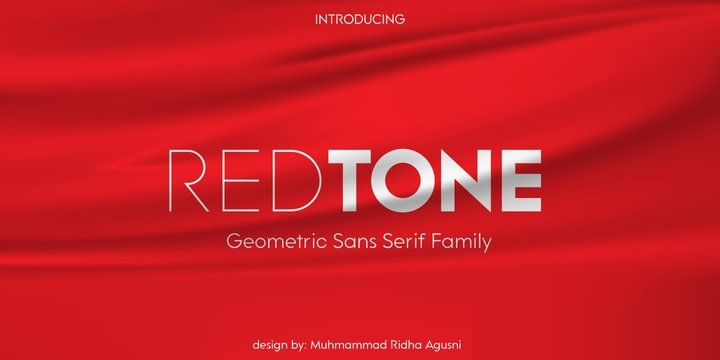
Redtone - это семейство геометрических шрифтов Sans serif, сочетание прямых линий и идеальных кругов с острыми краями. этот геометрический шрифт идеально подходит для любого дисплея.
В этом шрифте 14 шрифтов, состоящих из 7 начертаний от тонкого до жирного с соответствующим наклонным начертанием.
Шрифт Redtone имеет расширенный набор символов для поддержки языков Центральной и Восточной Европы, а также Западной Европы.
Этот шрифт отлично подходит для логотипов, упаковки, поздравительных открыток, презентаций, заголовков, надписей, плакатов, брендинга, цитат, заголовков, журналов, заголовков, веб-макетов, мобильных приложений, художественных цитат, типографики, рекламы, приглашений, дизайна упаковки, книг, заголовков книг и многого другого.